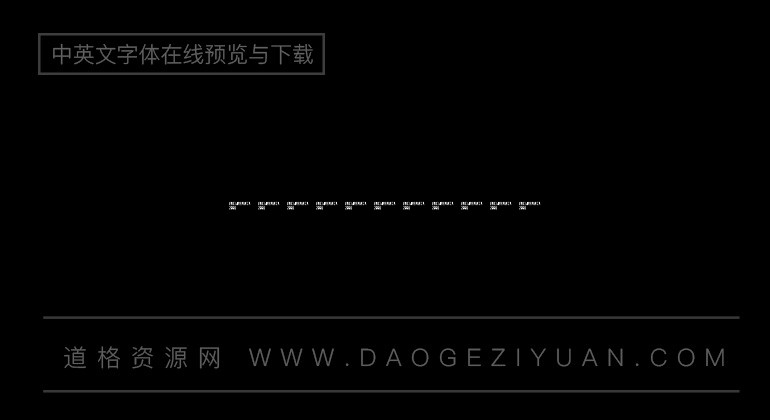
Citrus 2008 是一款由美国设计师 Lauren Thompson 创作的现代字体。这款字体的特点是其圆润的外形,带有一定的柔和感和亲和力,非常适合用于设计卡通、插画、广告以及包装设计等需要活泼、明快、有趣的场合。Citrus 2008 字体包括大写字母、小写字母、数字和标点符号,支持英文、西班牙文和法文等多种语言。同时,该字体具有多种字重和样式可供选择,可以满足不同设计需求。内容介绍
Citrus 2008是一款非常不错的手写艺术字体,具有很好的视觉感,适合于文化类的宣传设计、商业类品牌的广告和产品包装设计以及个性化文字排版等较多场景。